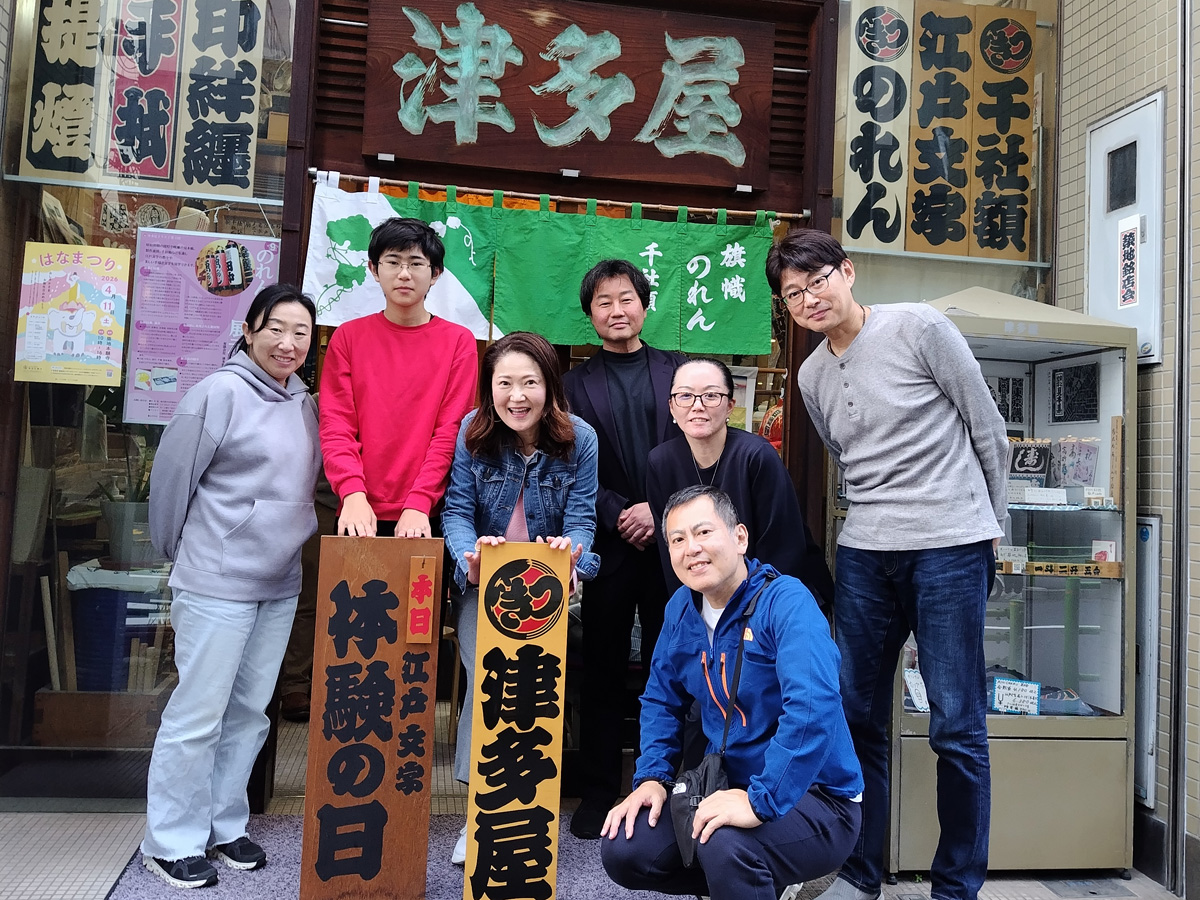
🖋職人の技をペンに乗せて。江戸文字の世界
今日のメインイベント「江戸文字の世界に触れる体験会」です。
講師にお迎えしたのは、築地で暖簾や提灯など制作されている津多屋商店店主の加藤木大介氏です。
江戸時代から続く、力強くも縁起の良い江戸文字の書き方を直接ご指導いただきました。
最初は「難しそう…」と緊張気味だった皆様も、いざペンを持つと表情は真剣そのもの。
自分だけの「文字」と向き合っていました。
出来上がった作品には、どれも参加者様の個性がキラリと光り、伝統文化の奥深さを肌で感じる貴重な時間となりました。